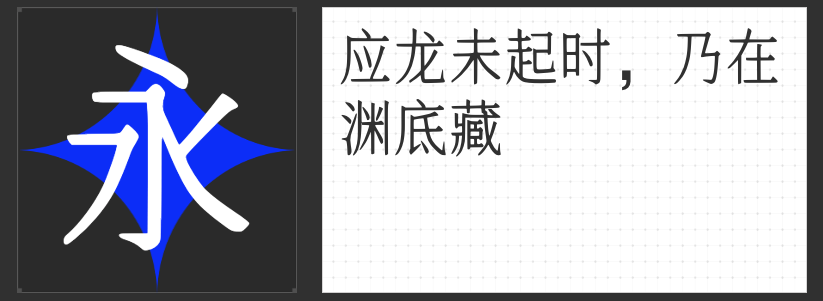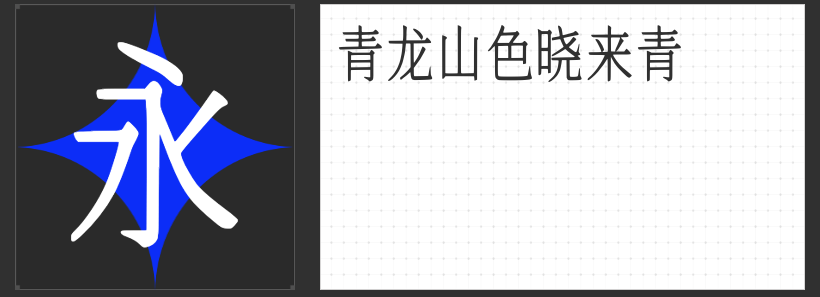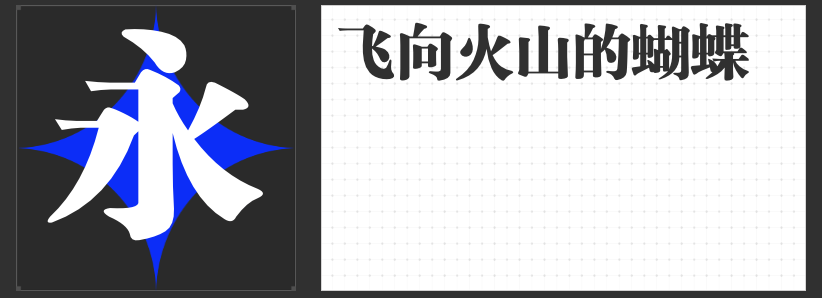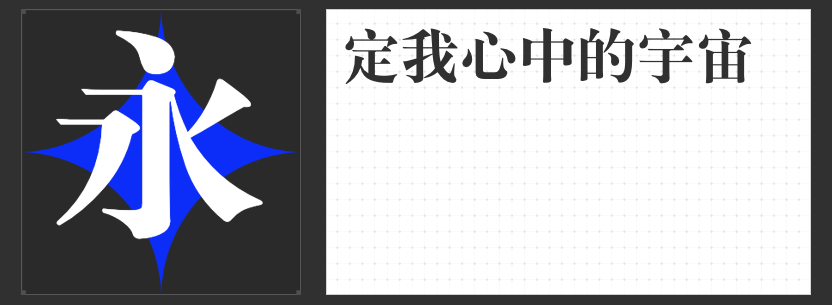
宋体新章:四款突破性字型重塑设计美学边界
在数字设计的浪潮中,宋体字正以多元姿态突破传统框架。这四款融合工艺美学与先锋思维的字型,既保留宋体基因中的典雅风骨,又以创新笔触开启视觉新境,为设计师提供更具张力的表达工具。
一、励字大标宋简繁
这款字型以"老宋体"为骨,注入黑体的现代筋骨,创造出独特的"双生体"结构。横细竖粗的经典比例中,三角状笔画端饰暗藏几何美学,尖端收笔既延续了雕版印刷的刀刻韵味,又通过数字化处理消除传统宋体的生硬感。其端正清秀的字形架构,在保持可读性的同时,为标题设计注入庄重而不失灵动的气质。
二、机甲宋青龙号
当宋体的婉约邂逅机甲的硬核,诞生了这款充满未来诗意的字型。设计师将装甲板的棱角转化为笔画转折处的金属切面,在竖画末端植入能量核心般的圆形装饰,使每个字符都成为微型机械生命体。这种刚柔并济的设计哲学,让青龙号既能驾驭科技主题海报,也可为传统文化展陈注入超现实质感。
三、机甲宋应龙号
应龙号通过横向压缩技术重塑宋体比例,创造出类似日式明朝体的修长体态。其独特的"机械衬线"设计——将传统宋体装饰角转化为可调节的模块化组件,使字体在不同字号下呈现迥异的视觉效果。这种弹性设计思维,为信息密集型排版提供了突破性的解决方案。
四、励字新粗宋简
这款字型以颠覆性思维重构宋体基因,将传统"扁方"结构拉伸为更具动态张力的几何形态。粗壮的竖画与纤细的横笔形成戏剧性对比,而刻意强化的尖端笔画则如书法飞白,在理性框架中注入即兴韵律。其打破常规的结体方式,为品牌标识设计开辟了充满实验性的创作路径。
这四款字型共同勾勒出宋体进化的可能轨迹——从物质媒介的刻痕到数字像素的重组,从文化符号的承载到设计语言的创新。它们证明,经典字体的生命力不在于固守形制,而在于持续与时代对话的勇气与智慧。